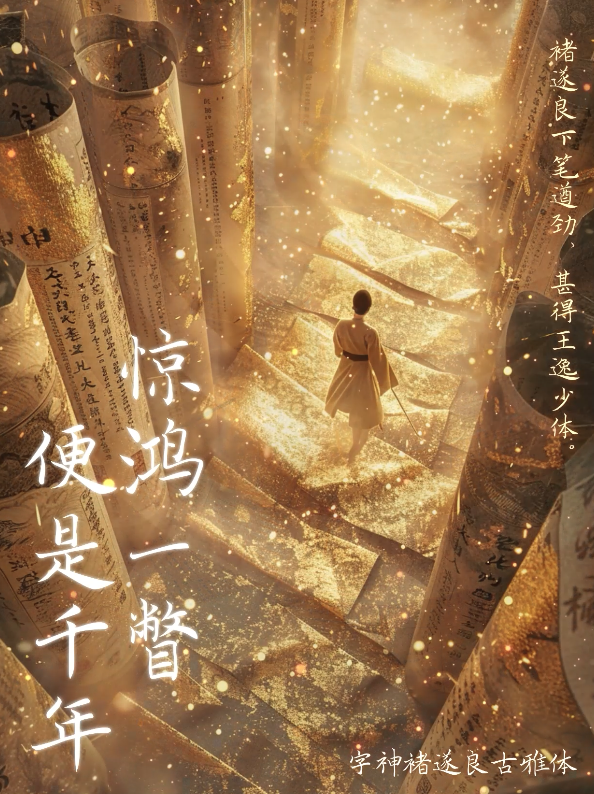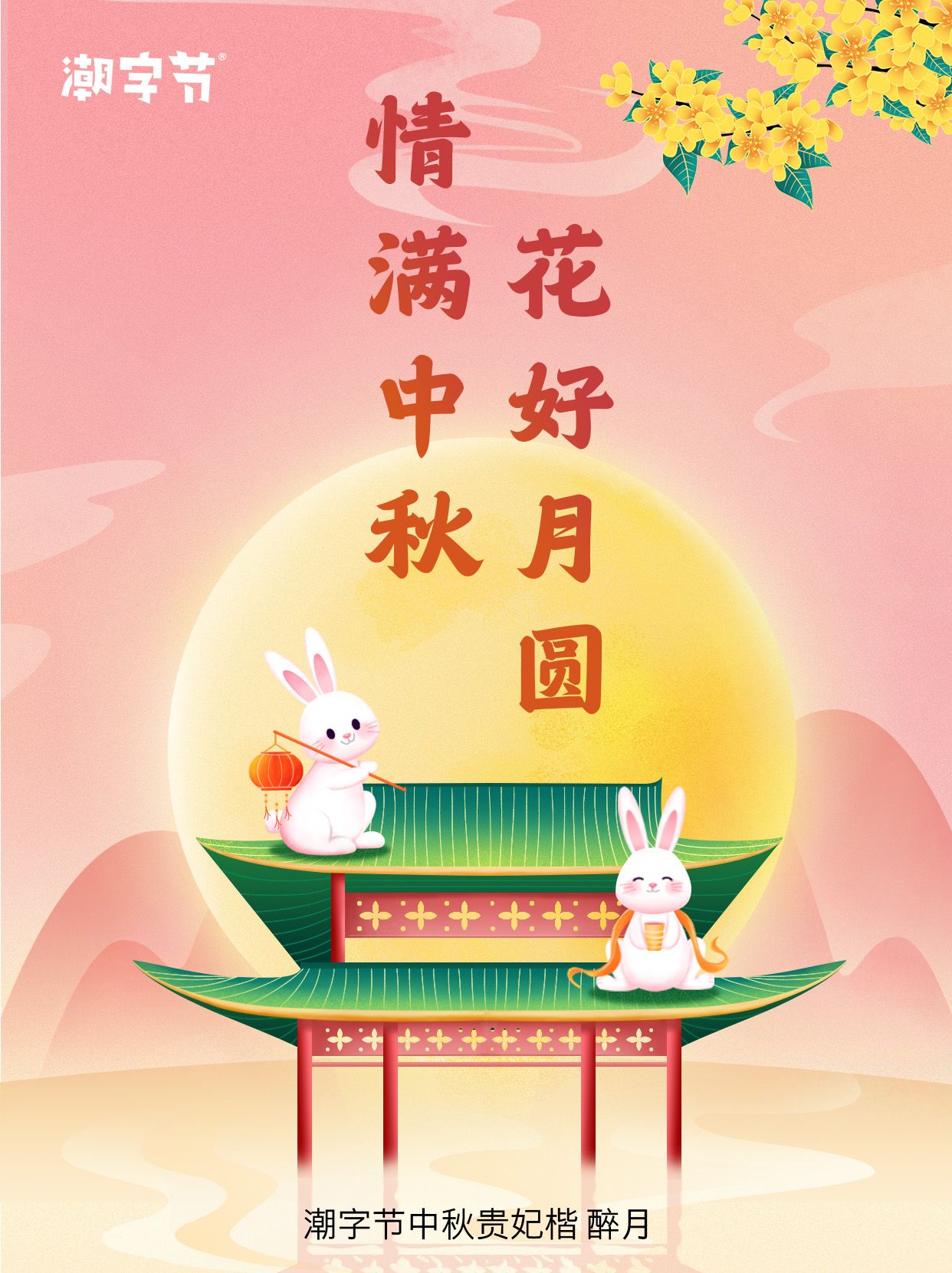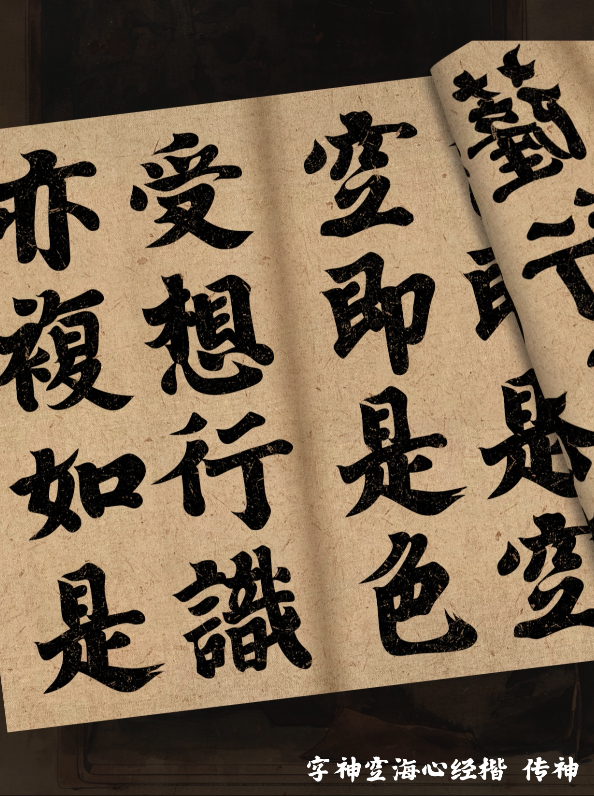
🔥穿越千年,唐风字体来袭!这三款字体让你秒变古风达人✨
古风热潮一直未减,而唐风更是其中的佼佼者。想要让你的设计作品或文案秒变古风,选对字体可是关键!今天,就给大家推荐三款超级适合唐风题材的字体产品,让你的作品瞬间提升格调!👑
🌟第一款:字神空海心经楷 传神
这款字体可是大有来头,它源自唐代高僧空海的《心经》楷书,字形端庄大方,线条流畅有力,每一个字都仿佛蕴含着千年的智慧与韵味。用它来书写唐风文案或设计作品,绝对能让你的作品传神入化,仿佛穿越回那个盛世大唐!🌸
🌙第二款:潮字节中秋贵妃楷 醉月
中秋佳节,怎能少了贵妃的陪伴?这款潮字节中秋贵妃楷字体,字形柔美细腻,线条宛如贵妃的轻纱舞动,充满了女性的柔美与温婉。用它来书写中秋相关的文案或设计作品,定能让你的作品醉人心扉,仿佛与贵妃共赏明月!🌙
🌿第三款:字神褚遂良古雅体 清秀
褚遂良是唐代著名的书法家,他的书法被誉为“古雅”。而这款字神褚遂良古雅体,正是对他的书法艺术的完美呈现。字形清秀雅致,线条流畅自然,每一个字都透露出一种超凡脱俗的气质。用它来书写唐风文案或设计作品,定能让你的作品充满书卷气,让人爱不释手!📜
三款字体,各有千秋,无论是想要表现唐风的庄重与大气,还是柔美与温婉,亦或是清秀与雅致,它们都能轻松驾驭。如果你也是古风爱好者,不妨试试这三款字体吧!让你的作品在小红书上大放异彩!✨